漢字の構成と制作ポイント03「横割り系」
今回は横割り系として、上下分割で構成される漢字の制作ポイントの紹介です。漢字の上側にあるものが「冠(かんむり)」、下側にあるものが「足(あし)」と呼ばれています。
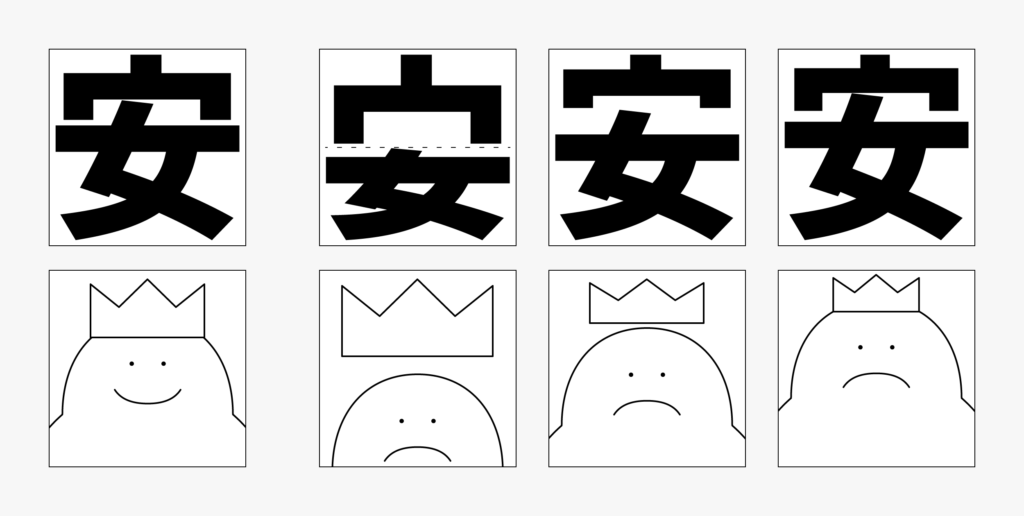
冠ではただ上下に並べるのではなく、被せる・中に入れるといったイメージで作る場合があります。例えば「安」なら「宀」の内側の空間に「女」の頭を食い込ませるようにして作り、見え方としては中の要素に冠が負けないよう調整しています。横割り系では横画が多くなりがちで、サンセリフ体のように横画も太さがある書体なら「上から下に少しずつ太めに作る」という原則を意識しています。ただし明朝体のように横画を均一の太さで作れる場合もあります。またこのグループは「吉責菫」のように左右対称のバランスを気に掛ける文字も他より多めです。